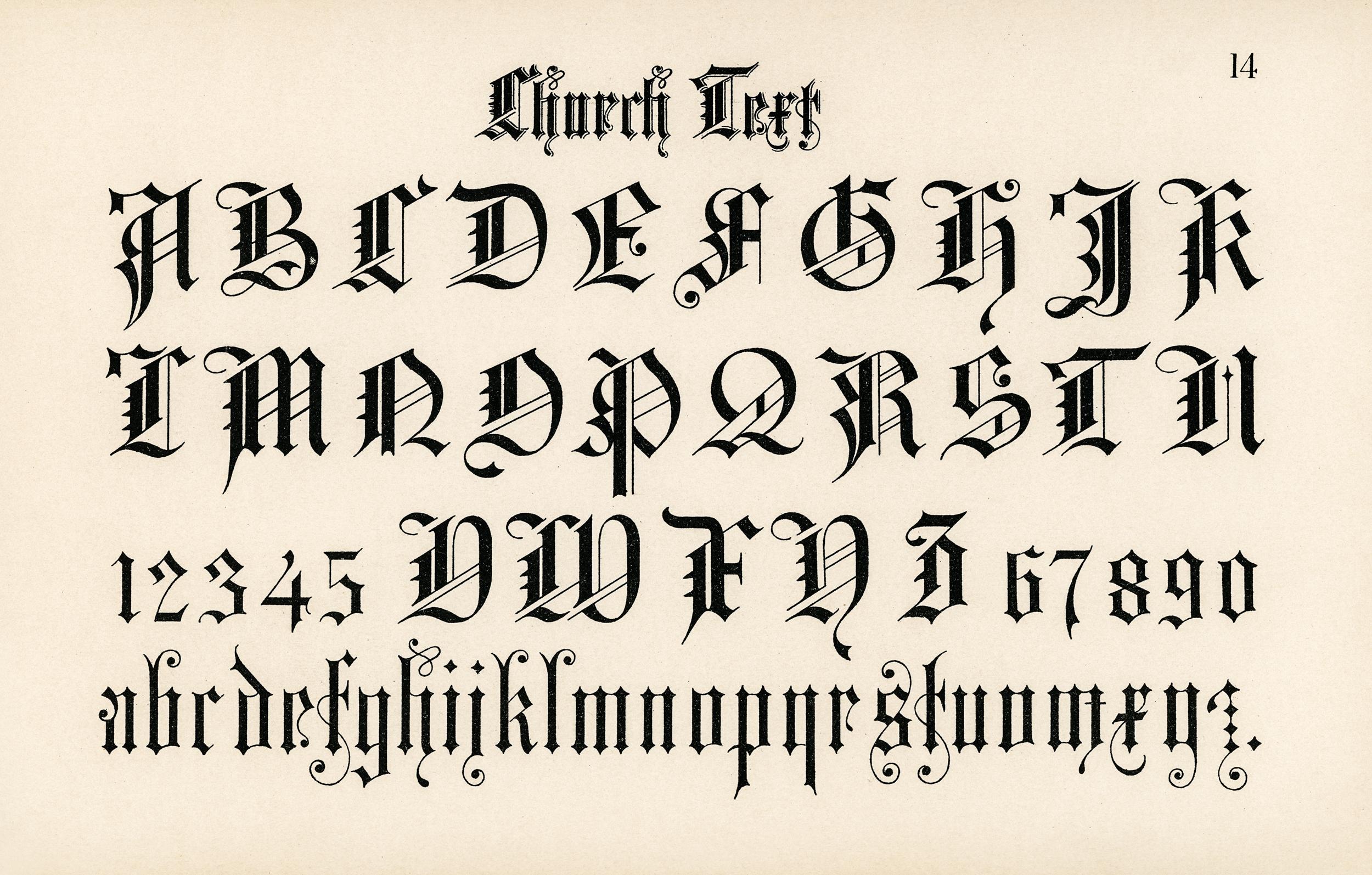
Готический шрифт. Всё, что о нём нужно знать каллиграфу
Готика — один из самых популярных каллиграфических шрифтов. Она эффектно выглядит, но использовать её нужно аккуратно – она трудно читается в больших количествах. Готика хорошо подходит для коротких крупных надписей, таких как:
- Заголовки статей
- Логотипы компаний или музыкальных групп
- Заголовки сертификатов, дипломов и других официальных документов
На самом деле готические шрифты подходят для любых целей, где важнее впечатляющий внешний вид нежели удобочитаемость.
Все готические шрифты содержат темные, плотные буквы драматичной формы. Они очень контрастны и украшены различными мелкими деталями. Общее ощущение от готического шрифта очень точно выразил великий Эдвард Джонстон в 1906 году:
«Правильно выполненный и используемый – это один из самых живописных стилей письма.
Противники Эдварда описывали этот шрифт менее поэтично, сравнивая его внешний вид с забором. Но это не мешает любителям готики считать её самым роскошным и чарующим стилем каллиграфического письма.
Если в готике использовать цвет, то лучше всего смотрятся традиционные цвета: глянцевый черный для основного текста, алый для прописных букв и заголовков, золотой для украшений. Такое сочетание делает даже современные надписи похожими на старинные:
Стоит отметить, что многие хэви-металл группы серьезно перебарщивают с готическим шрифтом, от чего он обретает комичный эффект. Это делает готику пригодной для пародий.
Основные навыки для качественного написания готических шрифтов:
- Угол наклона пера 45º
- Рисование прямых вертикальных линий
- Рисование коротких толстых и тонких диагональных линий в разных направлениях
- Резкие контролируемые росчерки пером
- Ритм
Вы найдете больше советов по написанию каждой буквы готического шрифта в серии пошаговых уроков.
В продолжении этой статьи мы подробнее познакомимся с историей готического шрифта.
Слово «Готика» происходит от названия исторического периода, когда такие шрифты использовались наиболее часто. Это примерно 1200 – 1500 годы.
Готику считают шрифтом немецкого происхождения. В Германии в плоть до XX века готические шрифты использовались в книгопечатании. До сих пор в Германии можно встретить вывески аптек, выполненные традиционным готическим шрифтом.
Готические шрифты в разной форме использовались по всей средневековой Европе. В основном это происходило в то время, когда готический стиль доминировал в архитектуре Западной Европы. Надписи в этом стиле имеют схожие черты с архитектурой того времени. Например сильным акцентом на вертикалях и обилием декоративных элементов.
Почему же он стал так популярен и сохраняет свою популярность в настоящее время?
Сегодня готические шрифты ценятся за свои яркие декоративные качества. Именно по этому его лучше использовать в чисто декоративных целях, где людям не так важно прочесть то, что написано.
Готический шрифт создает особое настроение средневековья и этот эффект очень любят каллиграфы.
И почему же средневековые монахи так полюбили именно этот шрифт?
Верите или нет, но это прежде всего вопрос экономии. Использование готического шрифта было гораздо дешевле, чем любого другого. Готические надписи имели плотную вытянутую вертикально форму отчасти как способ экономии пространства на листе. Его штрихи располагаются очень близко друг к другу, а это значит, что вы можете уместить больше слов в строке, больше строк на листе, больше текста в книге. В те времена книги в Европе писали на шкурах животных, а это дорогой материал. Использование готического шрифта позволяло значительно снизить затраты на производство.
Это означало, что стоимость книг становилась ниже, и больше людей могли себе позволить их покупать. Не случайно, что это был период расцвета книжного производства в Западной Европе.
Так что очень важно, что готика сделала книги доступнее. Готический период знаменит особенно маленькими копиями Библии, способными поместиться в небольшой карман.
Готический шрифт также использовался для копирования менее ценных книг, чем Библия. Нельзя назвать их дешевыми книгами, потому как большинство людей все равно не могли себе их позволить.
Однако, за свою экономичность готика расплачивается удобочитаемостью. Часто штрихи надписи в готическом стиле находятся так близко друг к другу, что буквы становится сложно прочесть.
Посмотрите на этот пример:
И это одна из причин возникновения во времена эпохи Возрождения в Италии нового стиля письма – гуманистический или Ренессанс рондо. Это шрифт с открытыми и изящными пышными формами. Смотрится чрезвычайно элегантно и легко читается.
Этот шрифт лег в основу многих современных печатных шрифтов, установил стандарты рукописного письма, но это уже другая история.
На этом я завершаю краткий обзор готического стиля. Чтобы иметь представление о происхождении и использовании готики этих знаний будет вполне достаточно.